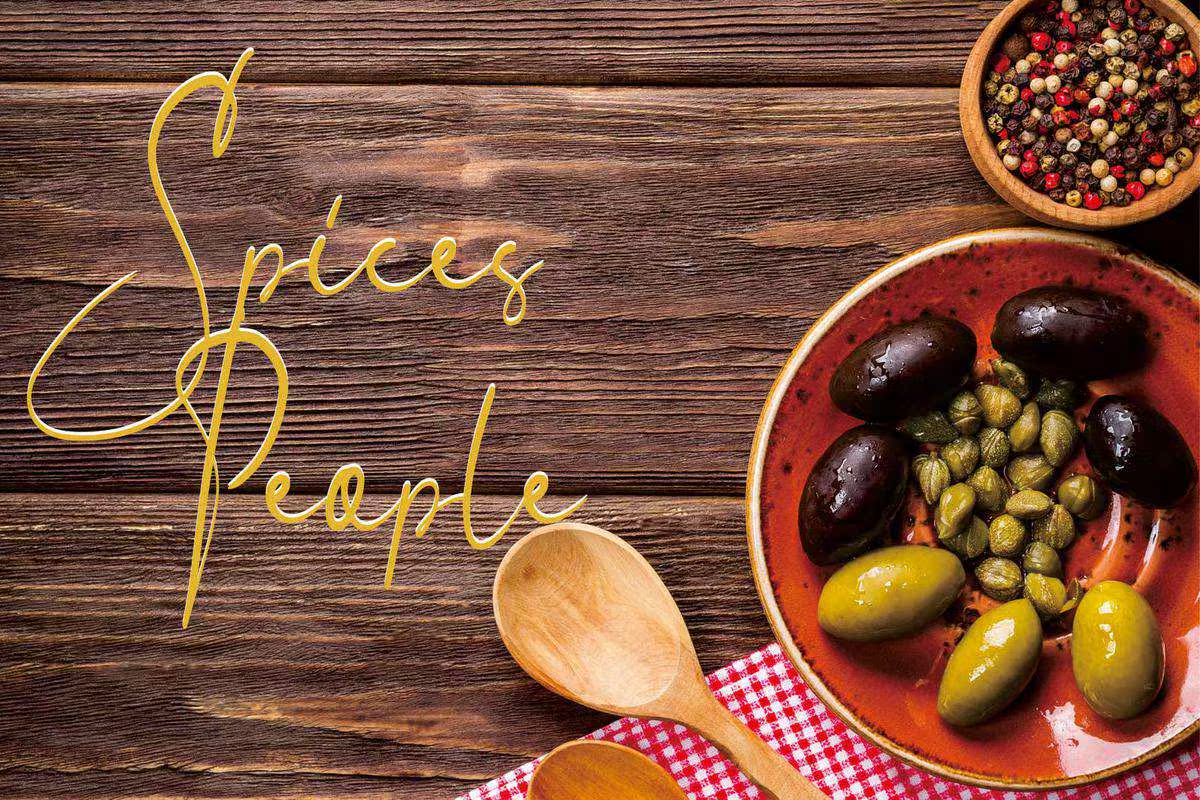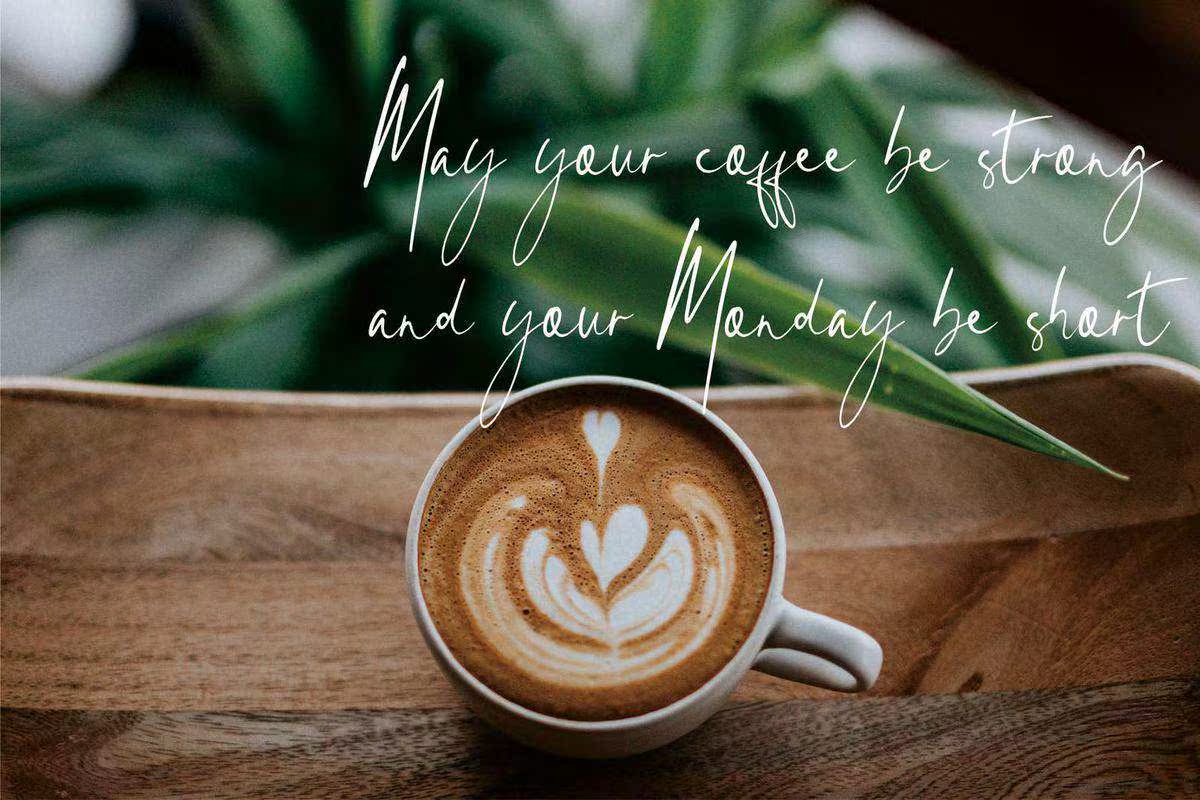
Queensbeachs Signatures A和Write Tensignature With Styleish Flow。此系列的脚本是完美的个人品牌。Queensbeachs Signatures完美的品牌项目、徽标、婚礼设计、社交媒体、广告、产品包装、产品设计、标签、照片、水印、邀请、,文具商和需要手写的项目品味。Queensbeachs Signatures A和Write Tensignatures With Styleish Flow。此系列的脚本非常适合个人品牌。Queensbeachs Signatures非常适合品牌项目、徽标、婚礼设计、社交媒体、广告、产品包装、产品设计、标签、照片、水印、邀请、,文具商和需要手写的项目。